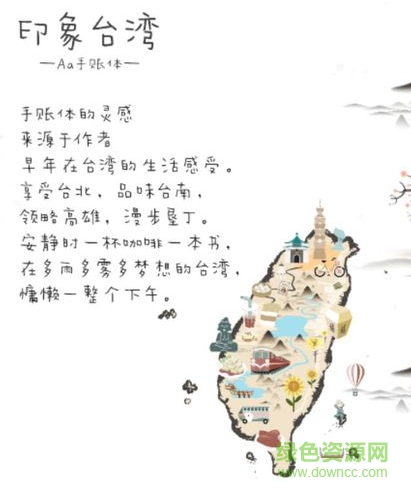
Aa印象手帳體ttf
Aa手帳體是由彎彎根據(jù)臺(tái)灣印象創(chuàng)作的藝術(shù)字體,如手帳記錄版的隨意和活動(dòng),感受安靜而又生趣的氣息在字里行間跳動(dòng),喜歡的朋友歡迎來(lái)綠色資源網(wǎng)免費(fèi)下載!
Aa手帳體的靈感來(lái)源于作者早年在臺(tái)灣的生活感受,享受臺(tái)北,品味臺(tái)南,領(lǐng)略高雄,漫步墾丁,安靜的額一杯咖啡一本書(shū),在多雨多霧多夢(mèng)想的臺(tái)灣,慵懶一整個(gè)下午!